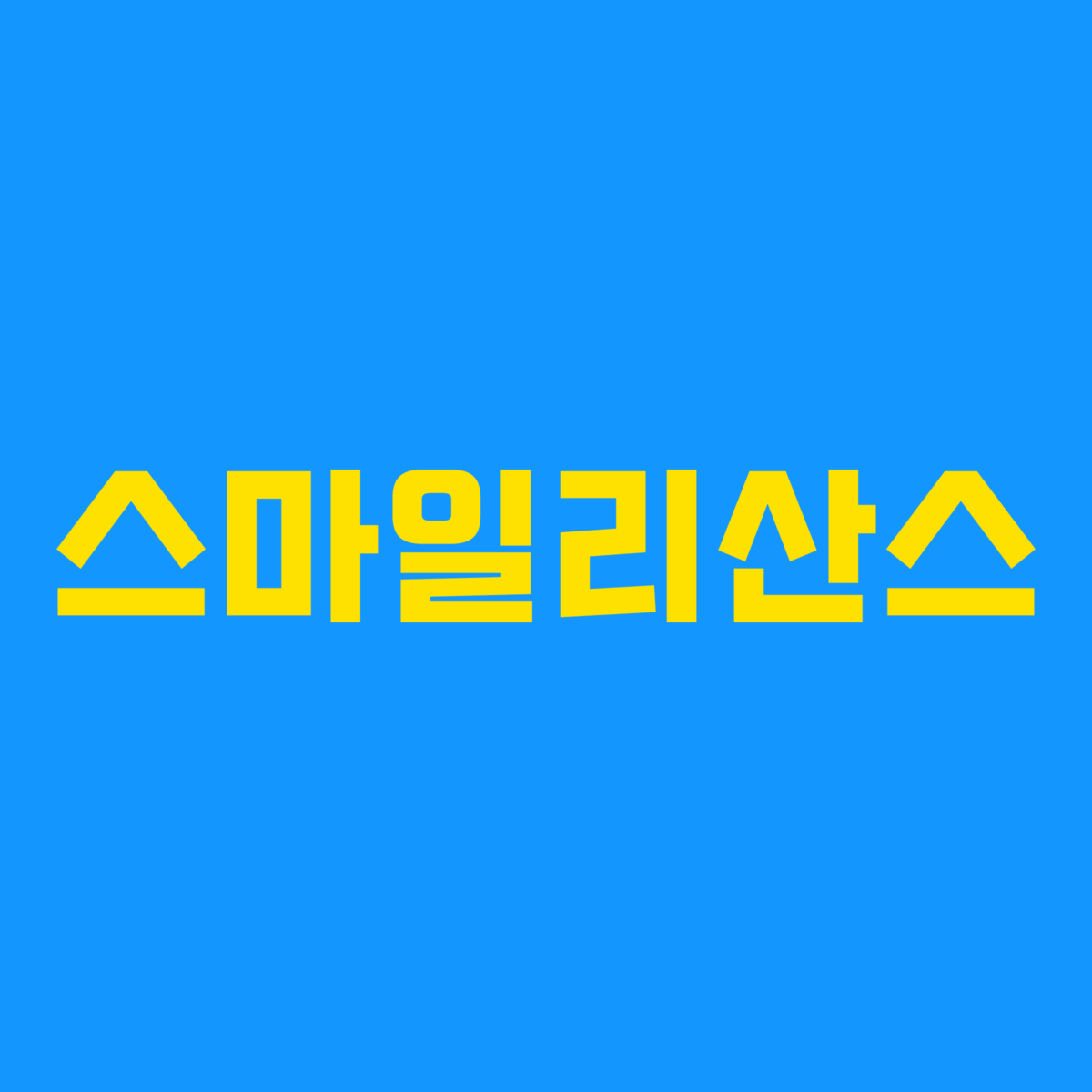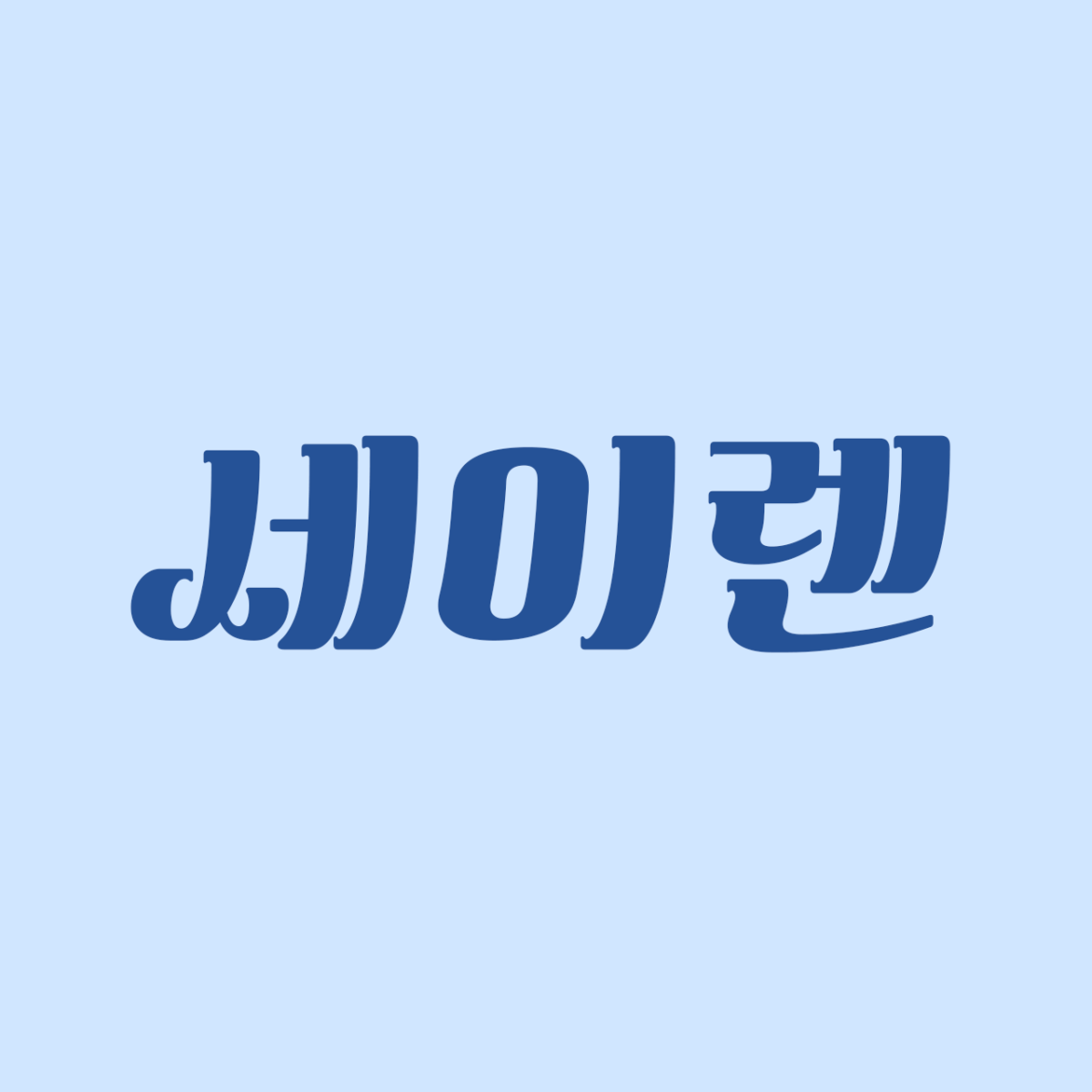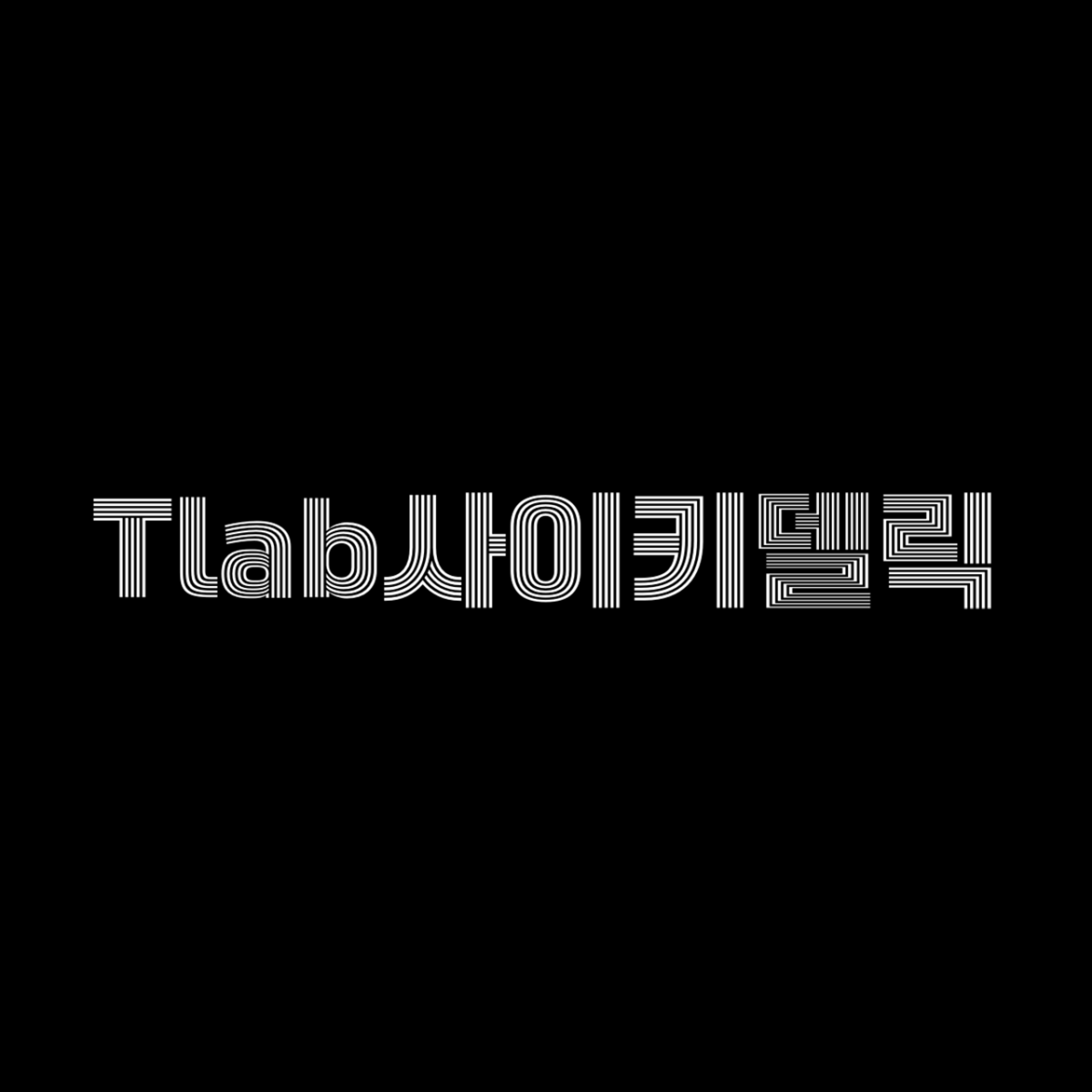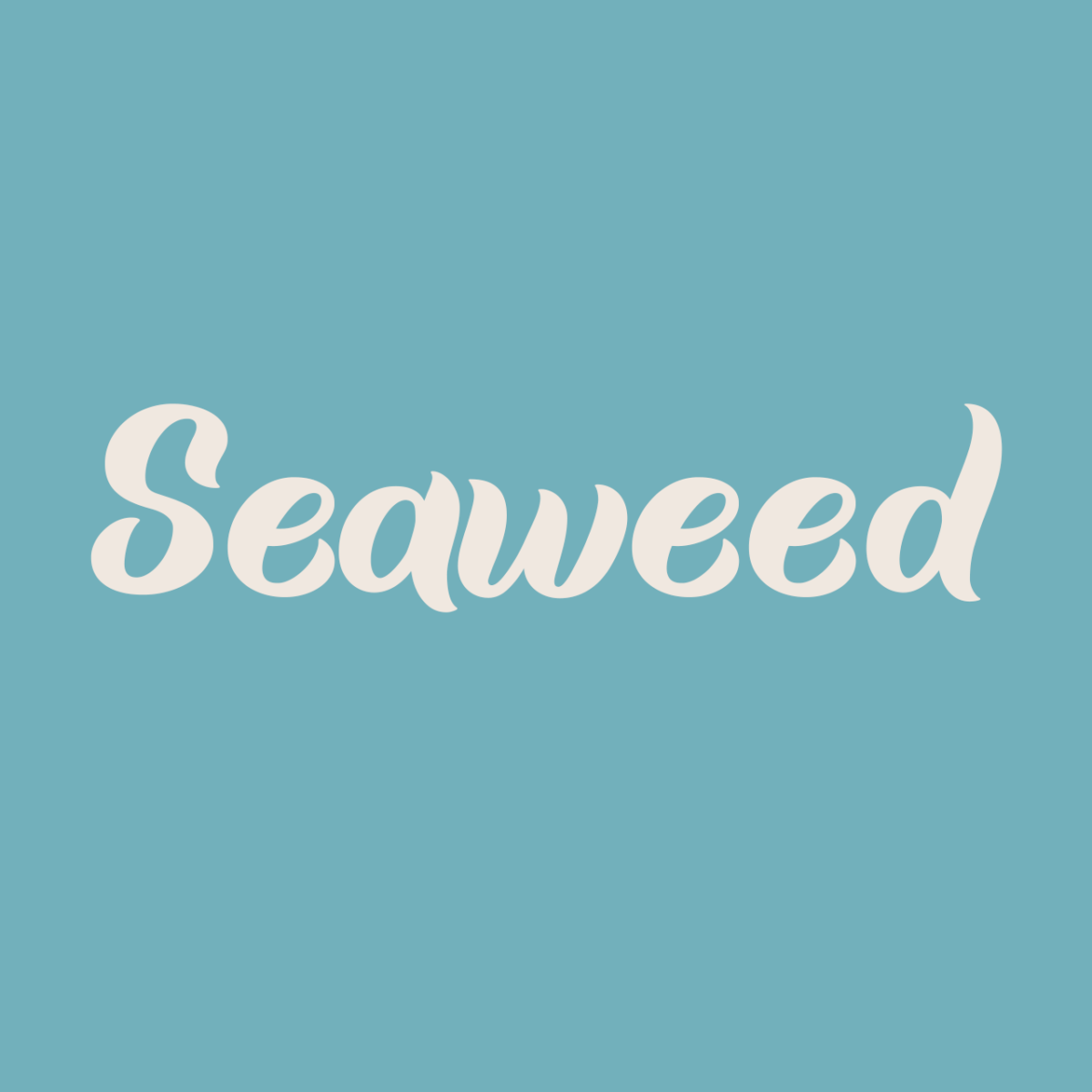
“보기만 해도 시원” 여름에 어울리는 폰트 추천
2024년 7월 산돌구름 추천 폰트 4선
올여름은 기온이 평년보다 높아 불볕 더위가 예상된다고 합니다. 잘 사용한 폰트는 콘텐츠에서 원하는 느낌과 전달하고자 하는 의도까지 뚜렷하게 담아낼 수 있는데요. 산돌구름이 보기만 해도 청량하고 시원한 느낌을 나타내는 폰트 4종을 소개합니다.
1. 산돌 / Sandoll 스마일리산스
Sandoll 스마일리산스는 지면에 꽉 차도록 디자인된 디스플레이용 폰트로, 어떤 환경에서도 선명하고 시원한 인상을 주는 폰트입니다. 특히 ‘ㅍ, ㅅ, ㅆ’ 등의 자소를 보면 미소를 닮은 듯한 형태가 특징이고, 숨어있는 스마일 표정이 귀여운 포인트랍니다. 이미지처럼 밝은 색상과 잘 어우러져 시원 상큼한 아이스 음료 패키지나 광고 영상에 활용해 보는 것을 추천해 드려요!
2. 지우소프트 / pln 세이렌
pln 세이렌은 물결과 같은 유려한 곡선을 사용하여 우아하고 세련된 인상을 주는 폰트입니다. 특히 자소 ‘ㅅ, ㅈ’의 곡선은 스퀘어 닙펜을 사용하여 파도처럼 유연하게 이어지는 획이 특징이죠. 획 대비와 기울기를 통해 주목성까지 높인 폰트로, 방송 타이틀이나 행사용 포스터에 크게 사용하시는 것을 추천 드립니다.
3.티랩 / Tlab사이키델릭
귀엽지 않고 강렬한 느낌의 제목용 폰트를 찾는다면 이 폰트를 주목해 주세요. 마치 특수 효과를 입힌 것처럼 폰트 그 자체로 그래픽 효과가 되는 Tlab 사이키델릭입니다. 획의 처음부터 끝까지 라인으로 이루어져 있어 특별한 디자인 없이 폰트만으로도 쉽게 제작물을 완성할 수 있어요. 화려하고 신나는 분위기의 페스티벌 포스터에 활용하면 한눈에 시선을 사로잡을 수 있겠죠?
4. 헬로폰트 / HelloFont ID Seaweed
이름부터 바다의 향기가 느껴지는 HelloFont ID Seaweed입니다. 시원한 물결이 치는 것처럼 표현된 폰트로, 자연스럽게 물의 이미지를 연상시켜 무더위를 날려버리는 시원한 느낌을 주죠. 단, 라틴 알파벳만 지원하는 폰트이기 때문에 ‘Summer’ ‘Sale’ ‘Hot’ ‘Event’ 등 이벤트 배너 등에서 강조하고 싶은 영문 텍스트에 적절히 활용해 보세요!